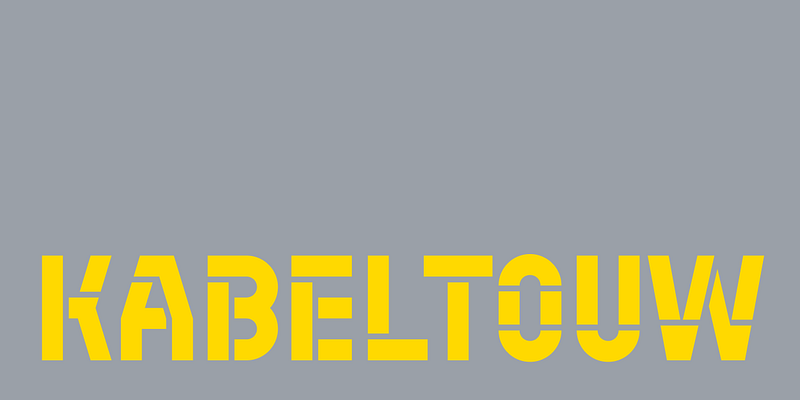
CoFo Kabeltouw は、重大な挑戦を恐れないモジュール式書体です。その工業的な外観は、コンテナ、貨物クレーン、カーブした金属パイプ、信号カラー、ステンシルテキスト編集、ピクトグラムなど、現代の海上輸送に基づいています。モジュールの数が限られているこの書体は、厳格な機械的なロジックと、手書きの文字のぬくもりを組み合わせています。書体の名前である Kabeltouw は、1/10 海里に等しい海上の長さの単位と、この長さの編組ケーブルに由来しています。CoFo Kabeltouw は、すべて大文字の設定でも認識できる特徴があり、代替文字の選択肢も豊富です (そのため、小文字がないことさえ感じさせません)。
Contrast Foundry は、あらゆる形態の書体をデザインすることに重きを置いたスタジオです。
このスタジオは 2014 年に Maria Doreuli によって設立され、Liza Rasskazova とのコラボレーションによって始められました。しかし、フォントのオンラインコレクションは 2018 年末にcontrastfoundry.com を通してのみ利用できるようになりました。Nikita、Anna、Egor、Anastasia、Tasya がスタジオに加わったため、ここ数年でフルタイムのチームメンバーは 2 人から 7 人に増えました。メンバー全員がデザインの経歴を持っていますが、専門分野はマネジメントからカリグラフィ、書体エンジニアリングまで多岐にわたります。
チームメンバーの拠点は別々の場所にあるかもしれませんが、それでも全員が緊密に連携しています。CoFo は海を越えて活動し、国境や時差などの障害を乗り越え、意欲的なメンバーで構成される強力なチームを作り上げています。CoFo の作品はコントラストの上に成り立っています。エキセントリックなディスプレイ書体とニュートラルでクラシックな書体の両方をデザインしています。デザイナーたちは小売用フォントに注力し、お客様のために挑戦的なカスタム書体やレタリングを作ることに情熱を注いでいます。